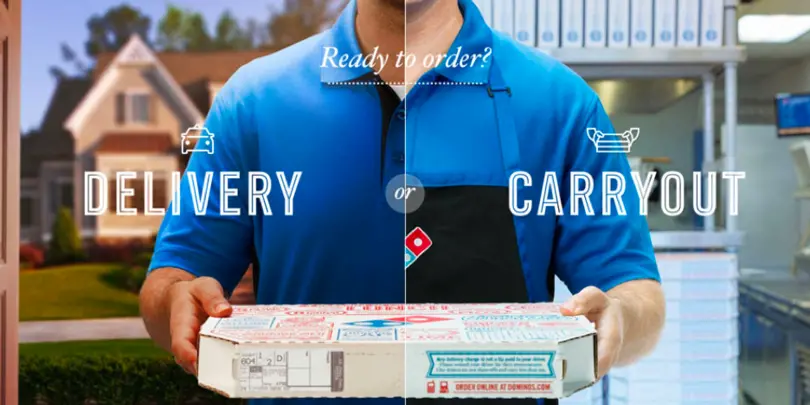
事例ご紹介:Pizza Press書体
Dominos
自由な組み合わせを可能にするモジュール式 マルチレイヤーフォントPizza Press書体
ドミノ・ピザを担当していたアメリカの広告代理店Crispin Porter + Bogusky社の依頼により、モノタイプの書体デザイナーのテランス・ワインジールが制作した書体のご紹介です。